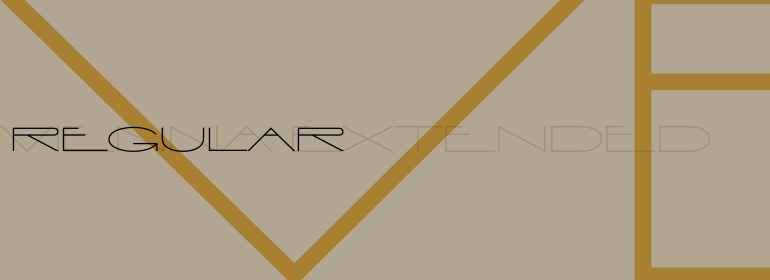
Vienna™ Extended
天才的加拿大平面设计师Antony De Meester创作了这个轻巧,优雅的无衬线字体。尽管简单是此设计的标志,但可以在需要富丽堂皇的外观时最有效地使用它。
Talented Canadian graphic designer Antony De Meester created this light, elegant sans serif typeface. Although simplicity is the hallmark of this design, it can be used most effectively where a look of regal elegance is desired.